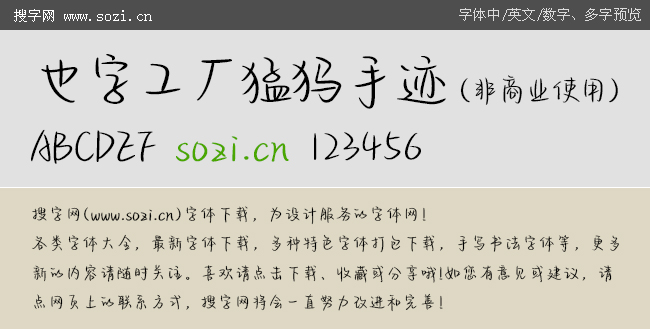
也字工廠猛犸手跡
搜字網(wǎng)給大家提供一款也字工廠猛犸手跡(非商業(yè)使用)中文字體下載,也字工廠猛犸手跡是一款手寫書法字體,字體書寫流暢,自然大方,具有很好的視覺效果。適合應用于書籍畫冊、海報、網(wǎng)頁設(shè)計等應用(此字體為個人非商用版,商用可以聯(lián)系:官方網(wǎng)址:https://yefont.com/home,聯(lián)系方式:13798980448)。